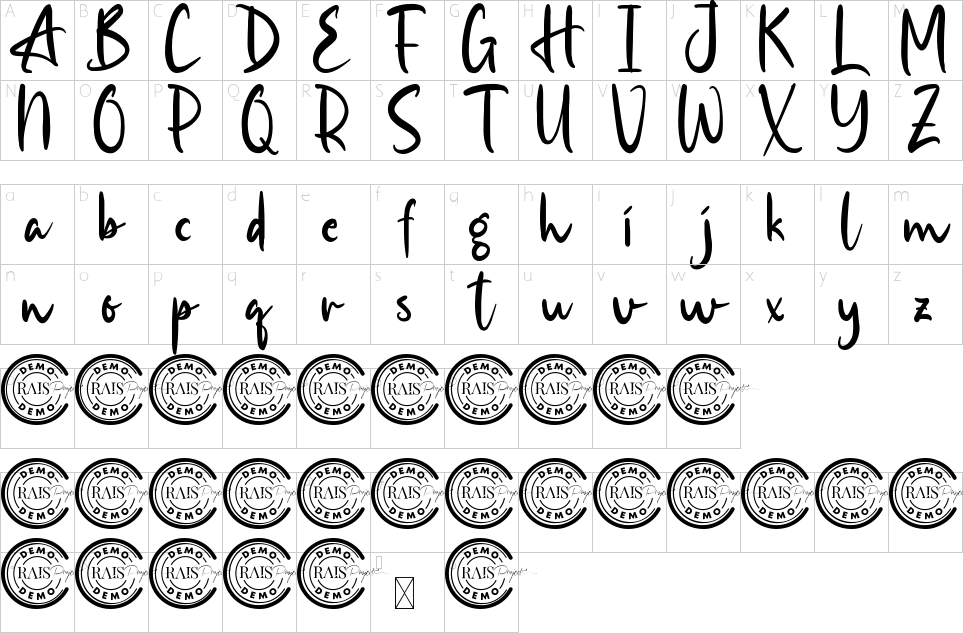
Ariella Hailey Font
Descubra a beleza da Ariella Hailey font para usar em seu próximo projeto de design. Esta fonte foi criada por RaisProject, uma equipe dedicada que busca manter a originalidade e a qualidade em cada projeto. A Ariella Hailey foi projetada para oferecer uma combinação harmônica de estilo e leitura confortável, tornando-a uma escolha popular para designers de sites, designers gráficos e até mesmo para aqueles que buscam uma fonte para uso pessoal. Com 2,615 downloads desde sua disponibilização, é evidente que a fonte atraiu designers de todos os níveis, desde aqueles que buscam um desafio para a sua paleta de fontes até aqueles que buscam uma fonte perfeita para um projeto específico. Seja para criar uma marca única, desenvolver um layout de newsletter ou simplesmente dar um toque especial a um documento, a Ariella Hailey font pode ser a solução perfeita. Combinada com sua facilidade de leitura, a fonte oferece um toque de sofisticação e elegância para qualquer projeto.
Mapa de caracteres da fonte Ariella Hailey Font